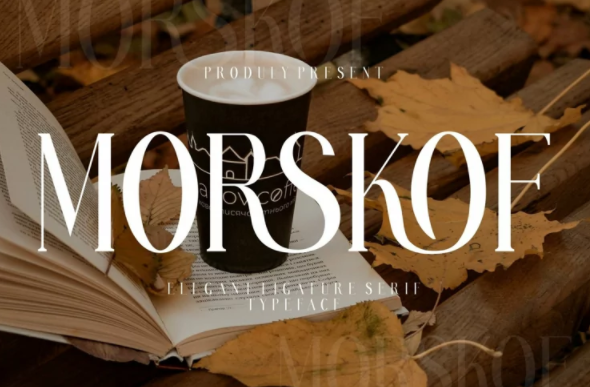
MORSKOF - элСгантный ΠΈ ΡΡ‚ΠΈΠ»ΡŒΠ½Ρ‹ΠΉ ΡˆΡ€ΠΈΡ„Ρ‚ с засСчками - этот ΡˆΡ€ΠΈΡ„Ρ‚ ΠΎΠ΄Π½ΠΎΠ²Ρ€Π΅ΠΌΠ΅Π½Π½ΠΎ соврСмСнный ΠΈ Π½ΠΎΡΡ‚Π°Π»ΡŒΠ³ΠΈΡ‡Π΅ΡΠΊΠΈΠΉ ΠΈ ΠΎΡ‚Π»ΠΈΡ‡Π½ΠΎ ΠΏΠΎΠ΄Ρ…ΠΎΠ΄ΠΈΡ‚ для Π»ΠΎΠ³ΠΎΡ‚ΠΈΠΏΠΎΠ², ΠΆΡƒΡ€Π½Π°Π»ΠΎΠ², ΡΠΎΡ†ΠΈΠ°Π»ΡŒΠ½Ρ‹Ρ… сСтСй. Они ΡƒΠΆΠ΅ ΠΏΠΎΠ΄ΠΎΠ±Ρ€Π°Π½Ρ‹ ΠΈ Π³ΠΎΡ‚ΠΎΠ²Ρ‹ ΠΊ использованию для вашСго ΡΠ»Π΅Π΄ΡƒΡŽΡ‰Π΅Π³ΠΎ Π΄ΠΈΠ·Π°ΠΉΠ½Π°! Для Ρ‚Π΅Ρ… ΠΈΠ· вас, ΠΊΡ‚ΠΎ нуТдаСтся Π² элСгантном, ΡΡ‚ΠΈΠ»ΡŒΠ½ΠΎΠΌ, ΡˆΠΈΠΊΠ°Ρ€Π½ΠΎΠΌ ΠΈ соврСмСнном Π΄ΠΈΠ·Π°ΠΉΠ½Π΅, этот ΡˆΡ€ΠΈΡ„Ρ‚ создан для вас!
MORSKOF создан с использованиСм возмоТностСй OpenType ΠΈ Π²ΠΊΠ»ΡŽΡ‡Π°Π΅Ρ‚ Π»ΠΈΠ³Π°Ρ‚ΡƒΡ€Ρ‹, Ρ†ΠΈΡ„Ρ€Ρ‹, ΠΏΡƒΠ½ΠΊΡ‚ΡƒΠ°Ρ†ΠΈΡŽ, Π° Ρ‚Π°ΠΊΠΆΠ΅ ΠΏΠΎΠ΄Π΄Π΅Ρ€ΠΆΠΈΠ²Π°Π΅Ρ‚ Π΄Ρ€ΡƒΠ³ΠΈΠ΅ языки.